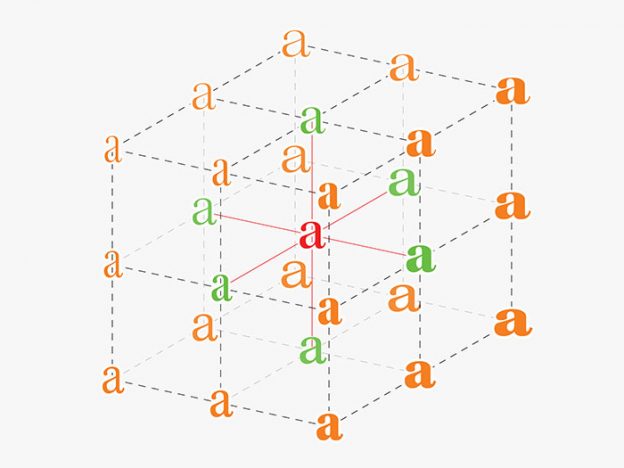
不同設備及系統的字體適配大概是設計師和前端們最頭疼的問題了,而微軟、蘋果等多家網路巨頭聯合開發的「 OpenType 可變字體」,有望拯救各位於水火之中。
上週,微軟在其印刷技術部落格(Typography)上宣布,他們與 Adobe、蘋果、Google 合作建立了一套增強版的 OpenType 字體。
OpenType 是微軟和 Adobe 在 19 年前共同開發的一種跨平台外框字體,而增強版的 OpenType,根據微軟部落格是這樣介紹的:
「OpenType 可變字體能讓網站設計者和應用開發人員在使用少量帶寬和小字體文件的情況下,獲得豐富多彩的排版體驗。可變字體也將為文檔創建者提供多樣化的排版選項,而無需管理上百個字體文件。可變字體將起到事半功倍的效果。」
通俗地講,每一種字體都包含有粗體、斜體等字級,而這些不同的變化都對應不同的文件,並佔據了不少空間。而 OpenType 可變字體則是將同一字體的所有訊息壓縮為一個文件,使得文件體積大為縮小,減少了對網頁帶寬的佔用,提升性能的同時,也能讓字體文件包含更多信息,解決字體在不同分辨率下的適配問題。
按照微軟的介紹,可變字體不僅包含有字級訊息,還能在斜體、粗體之間進行平滑連續的細微調整,比如:半加粗、稍濃等。這意味著網站開發者們可以根據頁面布局,對字體的寬度、標題、例寬等進行微調,而不需要留下大片難看的空白;另外,這一技術的應用,也能讓手機獲得優秀的瀏覽體驗,比如可變字體能自動調整大小以適應螢幕解析度和背景顏色等。
微軟希望在明年 Windows 中更新中實現 OpenType 可變字體的平台應用。而在此前的 Windows10 周年更新中,我們已經能在部分功能中見到這一字體的身影了。微軟表示將在未來幾個月內發布的 Windows 預覽版中,對可變字體提供更完整的功能支持。
其他參與本項目的公司也有各自的規劃,Google 則希望將其整合進 Chrome 瀏覽器及其 ASAP 字體中;Adobe 則也將於本月底發布可變字體的更新工具。